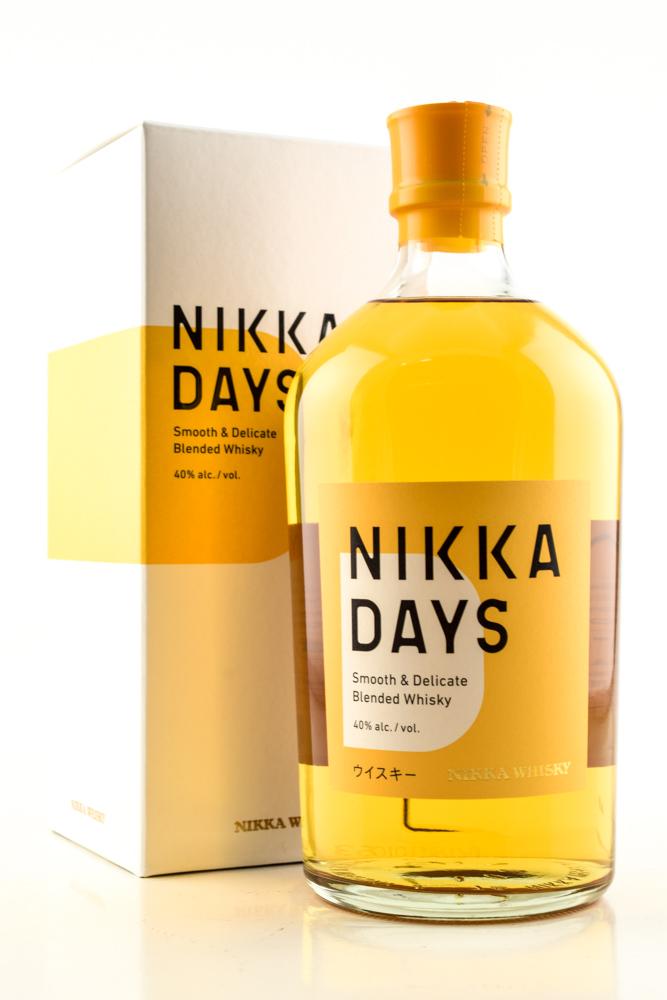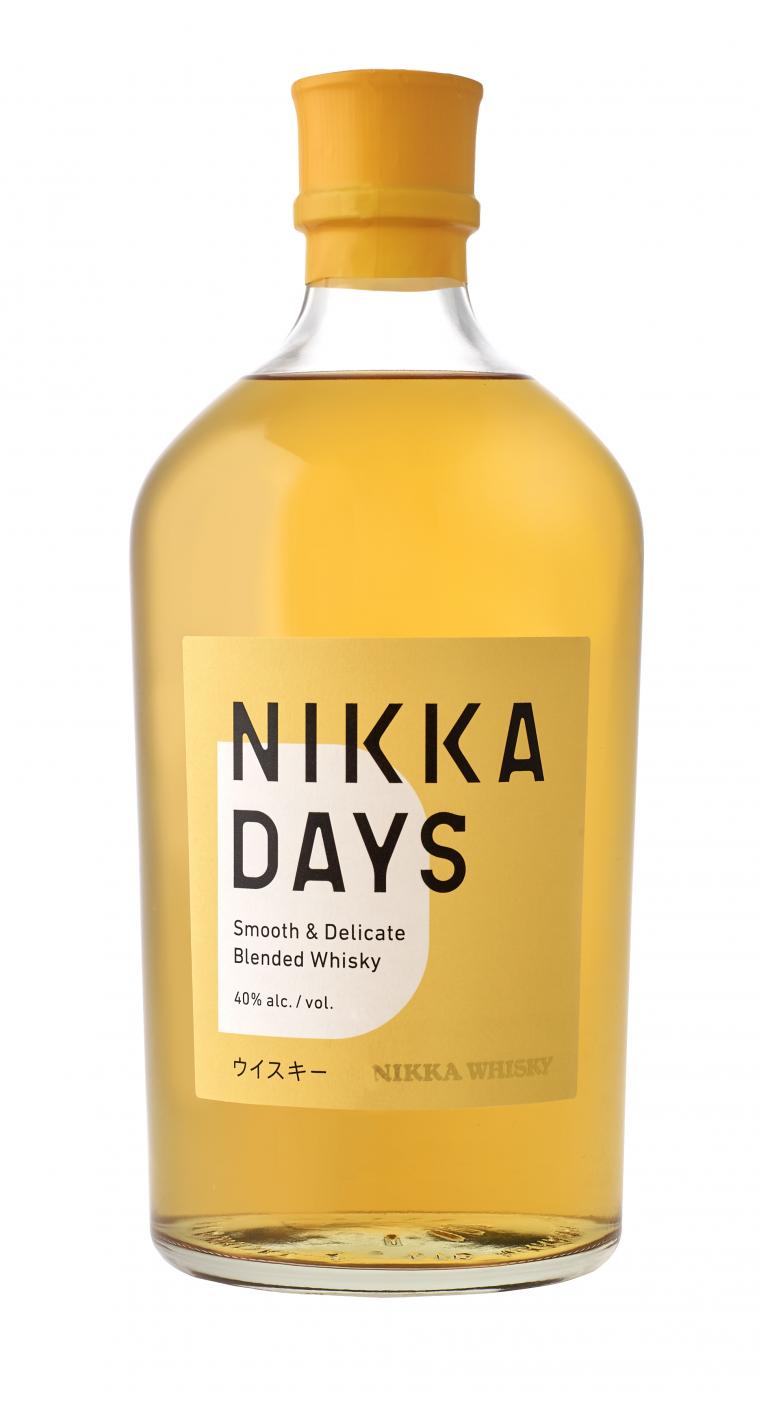
Schrift: Nikka Days Whisky
Achja, die Schrift kenne ich auch net! :-?
Das S hab ich auch schon mal gesehen, ich komm aber nicht drauf :cry:.
Hat da nicht einfach jemand die DIN 1451 verfremdet? Sieht für mich so aus: Das D hat die typische Außenkontur, das S die typische wohlgeformte Kurve. Wenn man beim N, A, D, Y der DIN-Schrift die Punzen rundet, beim K die zum Schaft führende Diagonale kappt und dem S einen Klotz verpasst, hat man die Schrift auf dem Etikett. Und ist der Rest nicht auch in der DIN-Schrift gehalten?
Maximal das D erinnert etwas an die DIN. Aber K, A und auch S sind doch komplett verschieden.:-?
Hmm, jetzt, wo ich ausgeschlafen bin und Du mir das Ding so groß vor die Nase hältst, nehme ich alles zurück und behaupte das Gegenteil.
Mir kam die Schrift aber ebenfalls unheimlich bekannt vor, und ich habe damit sofort Motorradkennzeichen assoziiert -- vielleicht liegt's daran?
Irgenwie kann ich mir bei diesem slab-semiserif -S schlecht vorstellen, daß das ein eigenständiger Font ist. Dürfte schon viel selbst Hand angelegt worden sein.
Ich finde es fällt nur das S aus der Reihe. Würde man, wenn man diesen Schriftzug bearbeitet nur diesen einen Buchstaben so speziell machen? Ich denke es ist irgendein verbastelter Freefont der vielleicht noch bei C oder G ähnliche Details wie beim S hat ...